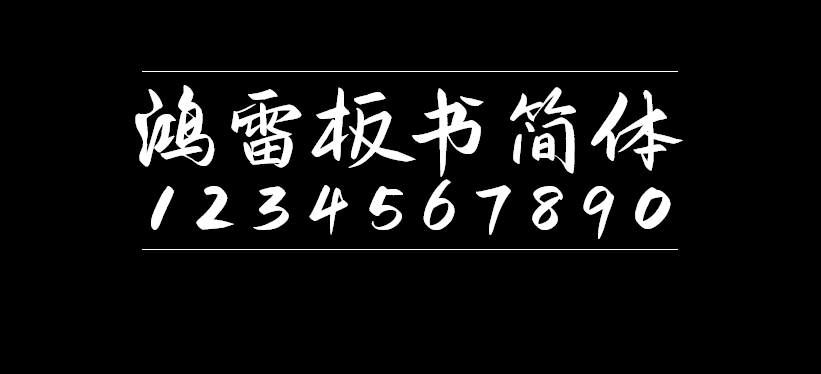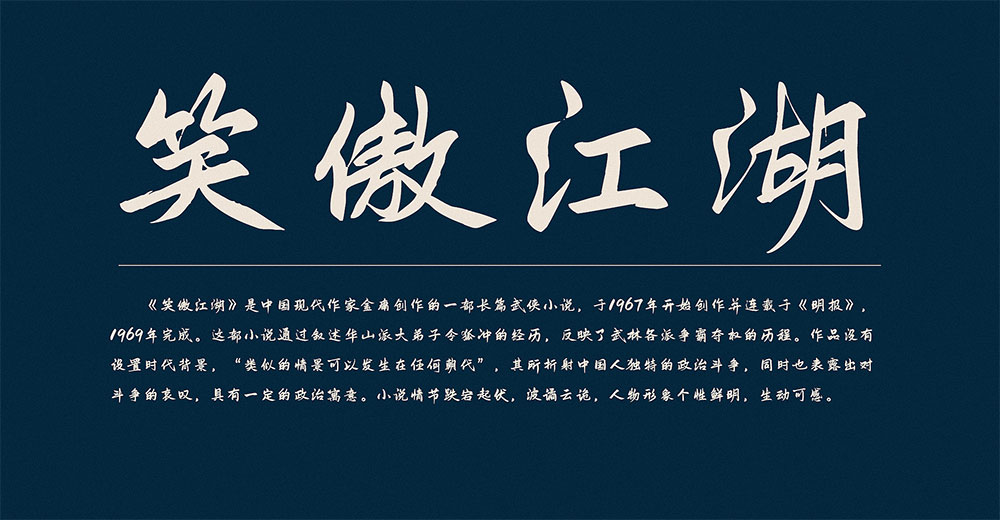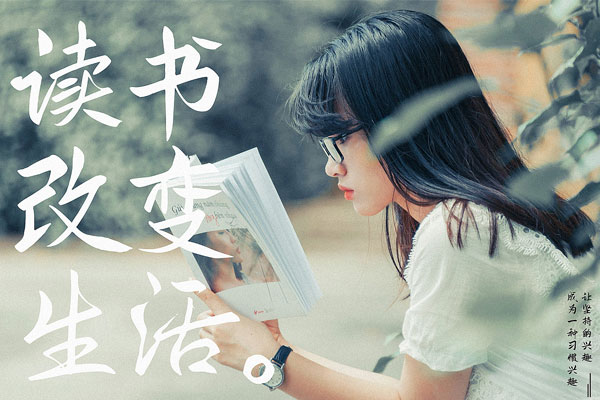
鸿雷板书简体
鸿雷板书简体是中国泉州设计师鸿雷创作的一款书法字体,发布于2020年4月8日,对于这款字体有任何问题,大家可以加一下作者鸿雷的微信公众号“鸿雷字迹”进行反馈。
鸿雷板书简体包含字符数量大约6800字,还是比较全的。字形潇洒飘逸,由于作者使用的是数位板书写,所以命名为“板书”。
鸿雷板书简体